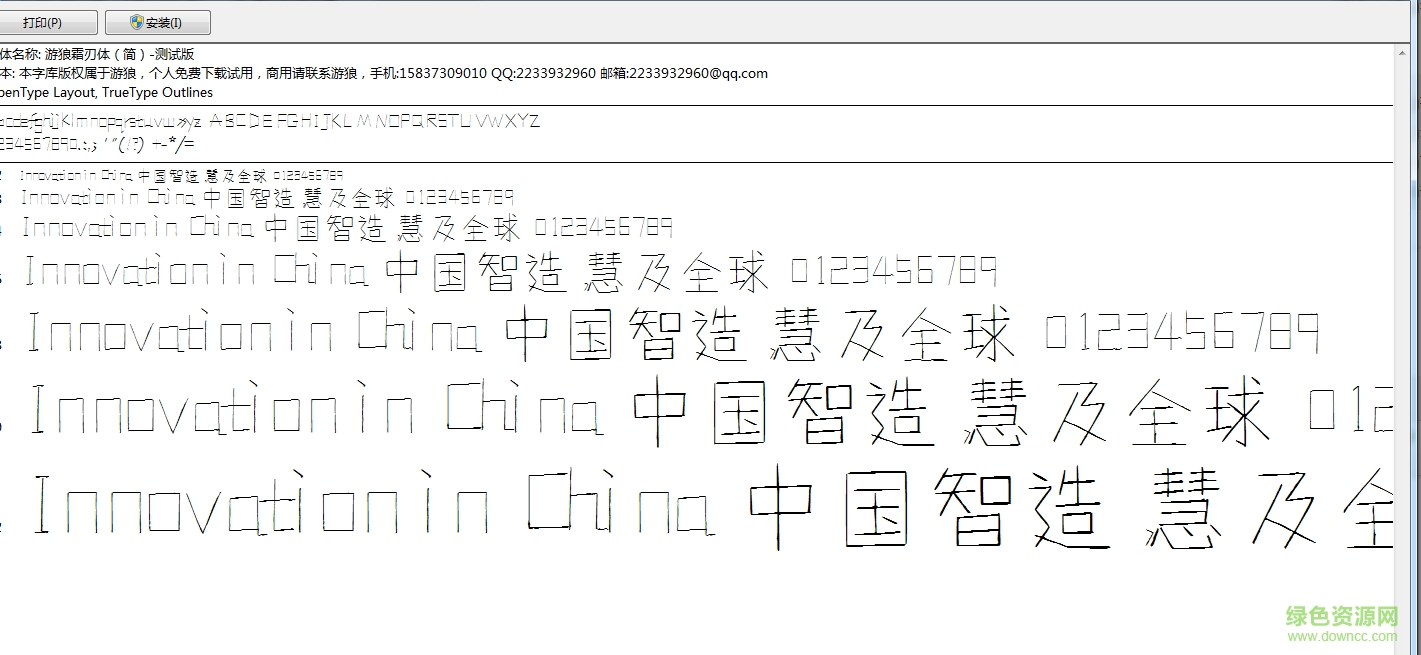
游狼鋒芒霜刃體是一款用于鉛筆設(shè)計(jì)方面的字體,凌波微步,羅襪生塵,隨意而為,洋洋灑灑,不拘一格!需要的朋友趕緊來(lái)綠色資源網(wǎng)下載喲!
游狼鋒芒霜刃體是一款筆畫(huà)橫折均勻的中文字體,這款字體筆畫(huà)較細(xì),有點(diǎn)像手寫(xiě)的感覺(jué),看起來(lái)比較的有創(chuàng)意,可以應(yīng)用于一些創(chuàng)意設(shè)計(jì)領(lǐng)域。